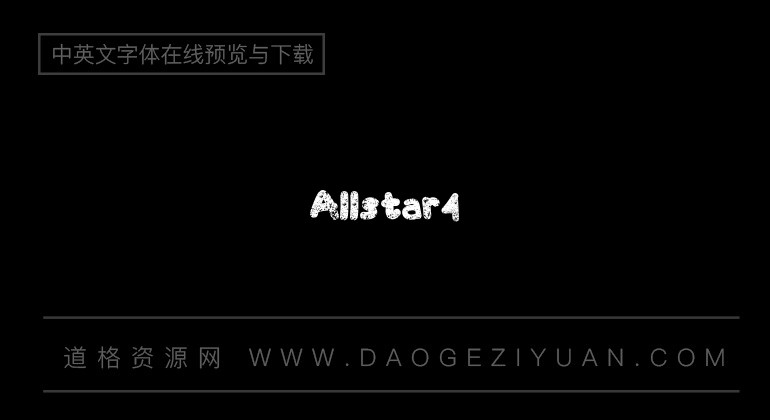
Allstar4
Allstar4 字体是一款比较流行的手写风格字体,它的设计师是Raki Yoshimura。这款字体具有非常明显的手写风格,每个字母的笔画都非常具有个性,有着非常明显的手写感。 Allstar4 字体的特点是比较圆润,线条非常的流畅,每个字母之间的间距也比较宽松,非常适合用于大标题、广告宣传、海报设计等需要突出效果的场合。另外,Allstar4 字体还带有一定的艺术气息,是一款非常适合用于设计类的项目的字体。 总之,Allstar4 字体的手写风格、流畅的线条以及艺术感都非常突出,是一款非常适合用于突出效果的大标题和海报设计等场合的字体。
Allstar4是一款非常不错的手写艺术字体,具有很好的视觉感,适合于文化类的宣传设计、商业类品牌的广告和产品包装设计以及个性化文字排版等较多场景。